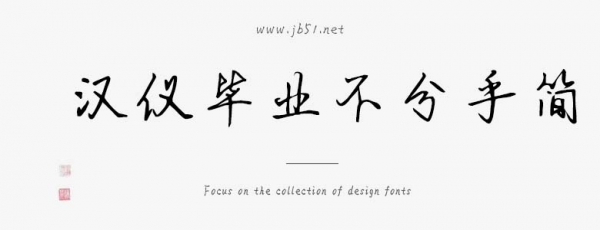
漢儀畢業(yè)不分手簡(jiǎn)是由漢儀字庫(kù)出品,字體筆觸纖細(xì),書寫流暢灑脫,適合應(yīng)用于藝術(shù)設(shè)計(jì)、平面宣傳設(shè)計(jì)、網(wǎng)頁(yè)設(shè)計(jì),書法字帖等領(lǐng)域,需要的朋友可以前來(lái)本站下載。